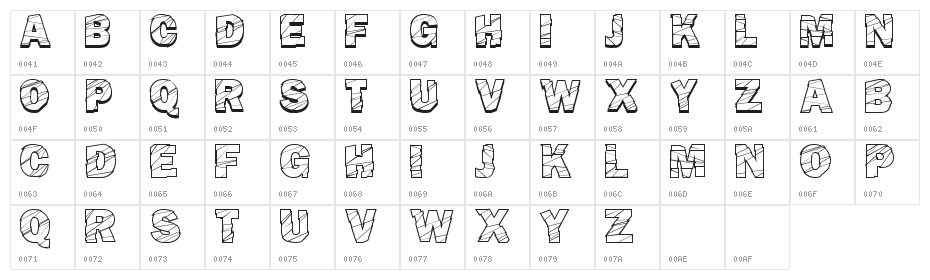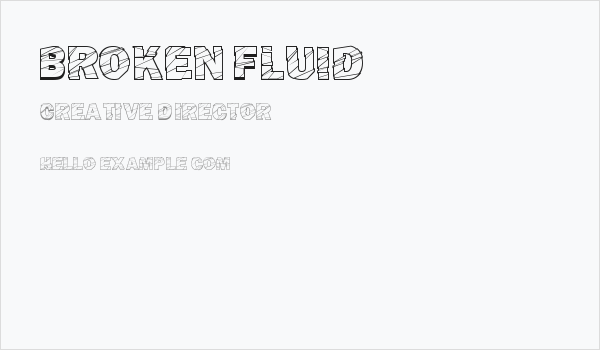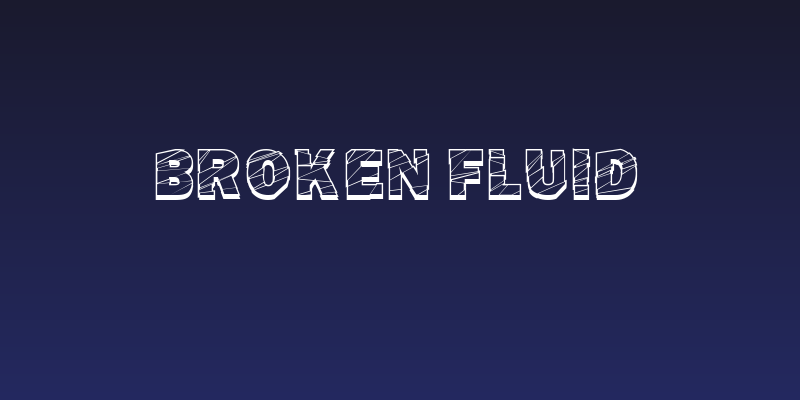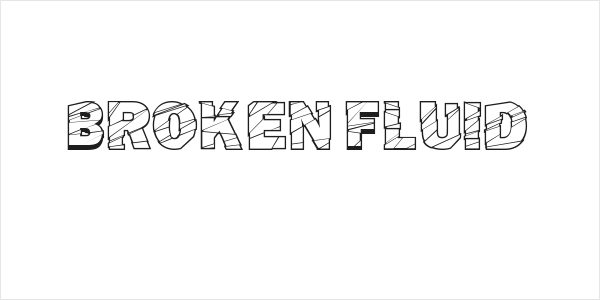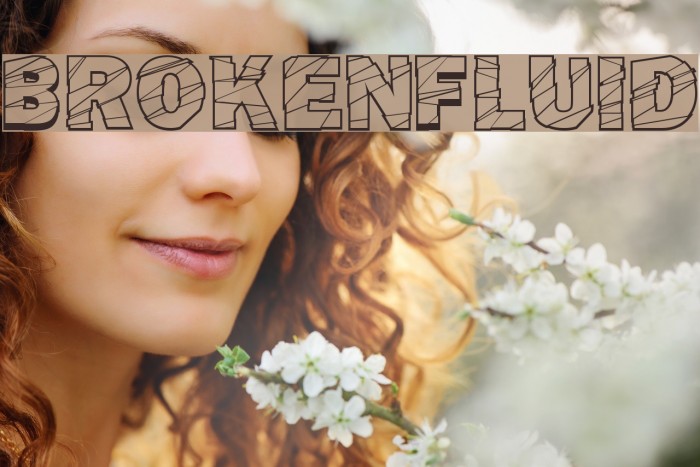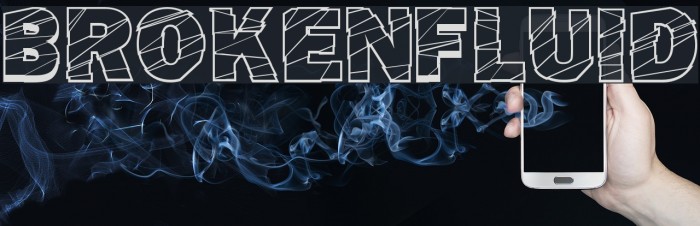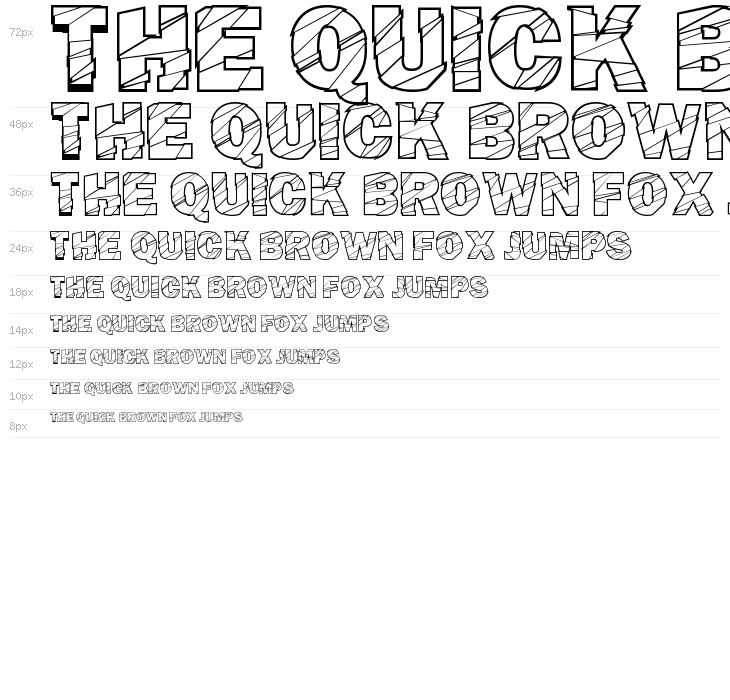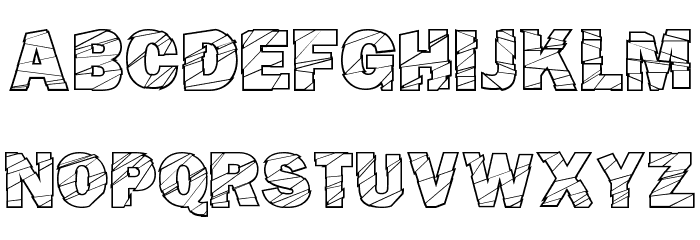
Broken Fluid Font
✎ Distorted Eroded
| Categorie | Distorted Eroded |
| Progetti proposti | Ideal for posters, album covers, branding, and any project requiring a bold, artistic statement. |